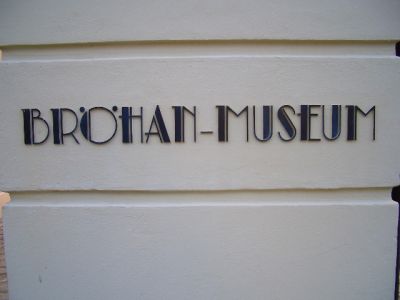
In meinen, vielleicht zu stark von der Schriftmalerei geprägten Augen steht das ‹U› hier falsch herum – was meint ihr ?
Hat sich halt mit dem „A" solidarisiert.
Seh ich genauso. Ist die Farbe auch unterschiedlich, oder wirkt das nur auf dem Foto so?
::]Ist die Farbe auch unterschiedlich, oder wirkt das nur auf dem Foto so?
Auf dem Photo sieht es tatsächlich so aus, als hätten die Buchstaben – nicht nur das ‹U› – verschiedene Farben. Es liegt aber eher an der unterschiedlichen Verschmutzung …